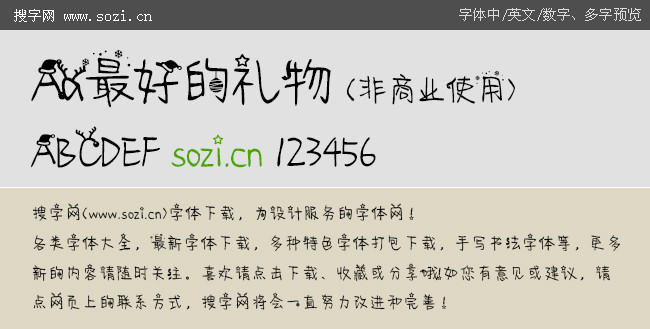
Aa最好的禮物(非商業(yè)使用)
搜字網(wǎng)給大家提供一款A(yù)a最好的禮物(非商業(yè)使用)中文字體下載,該字體是一款卡通中文字體,字形有趣可愛,并裝飾有卡通圖案,充滿童真,適合兒童包裝設(shè)計(jì)、書裝設(shè)計(jì)、海報(bào)設(shè)計(jì)等應(yīng)用(此字體為個(gè)人非商用版,商用可以聯(lián)系QQ:1006760504)。